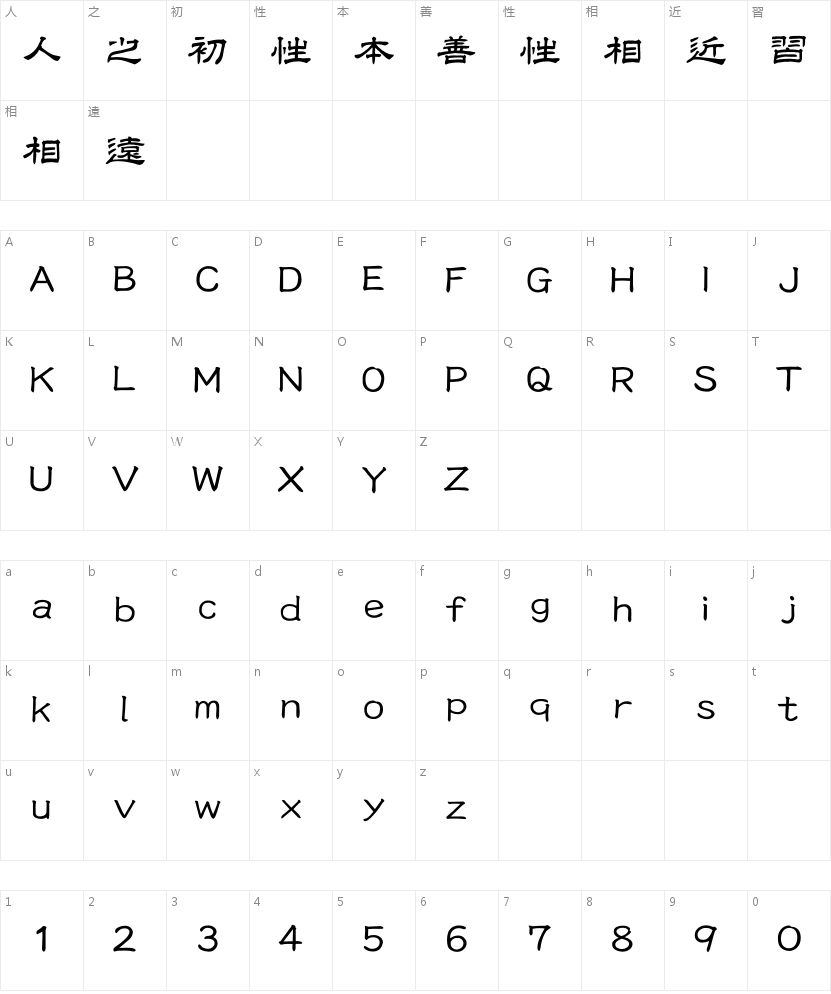
HOT-白舟隷書R Std 是一款非常優秀的日文字體,它的特點是簡潔大方,字體的線條清晰,字形精細,筆劃細膩,而且還具有良好的可讀性。這款字體可以幫助用戶創造出漂亮的日文文本,是一款非常棒的日文字體。內容介紹
HOT-白舟隷書R Std是一款非常不錯的手寫藝術字體,具有很好的視覺感,適合於文化類的宣傳設計、商業類品牌的廣告和產品包裝設計以及個性化文字排版等較多場景。